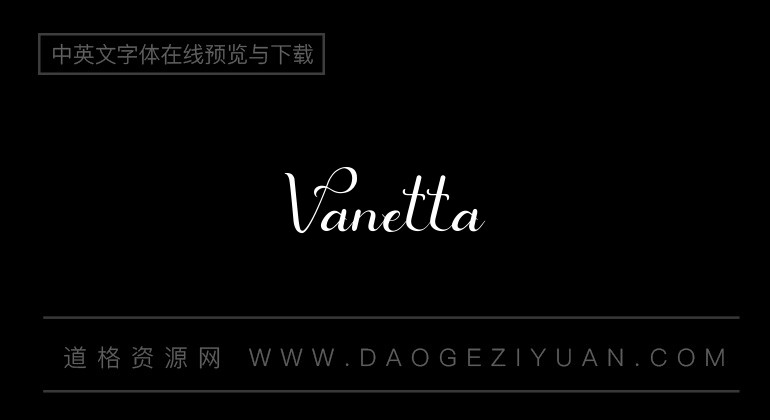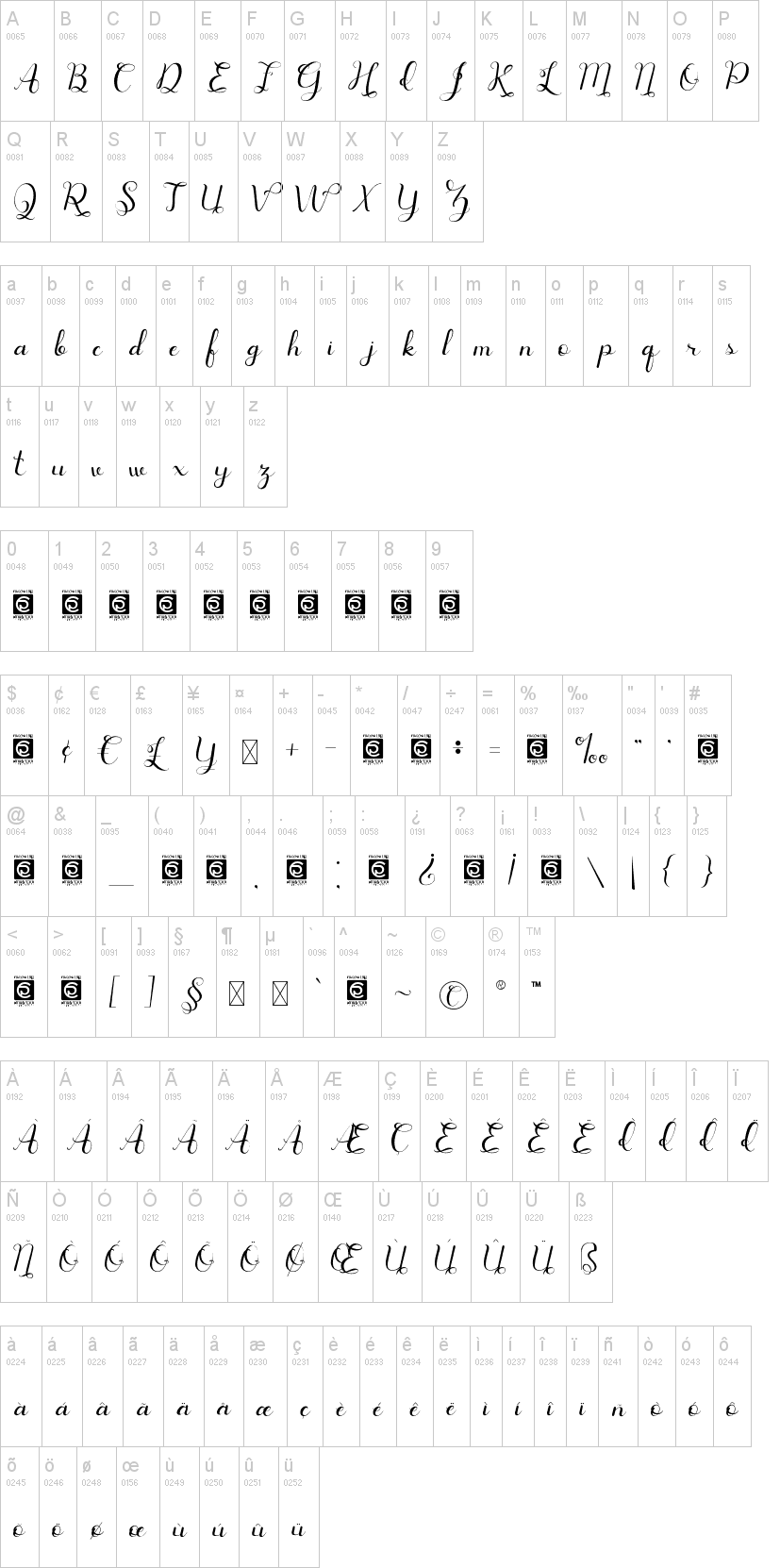
Vanetta 是一款时尚漂亮的字体,它具有细腻的笔画,柔和的边缘,以及明亮的外观。它可以用于各种类型的设计,从商业到时尚,都可以使用它。它的设计具有现代感,拥有一种柔和的气质,可以为任何作品添加精致的外观。它也是一款可调整大小的字体,可以调整字体大小,以适应不同的设计需求。内容介绍
Vanetta是一款非常不错的手写艺术字体,具有很好的视觉感,适合于文化类的宣传设计、商业类品牌的广告和产品包装设计以及个性化文字排版等较多场景。